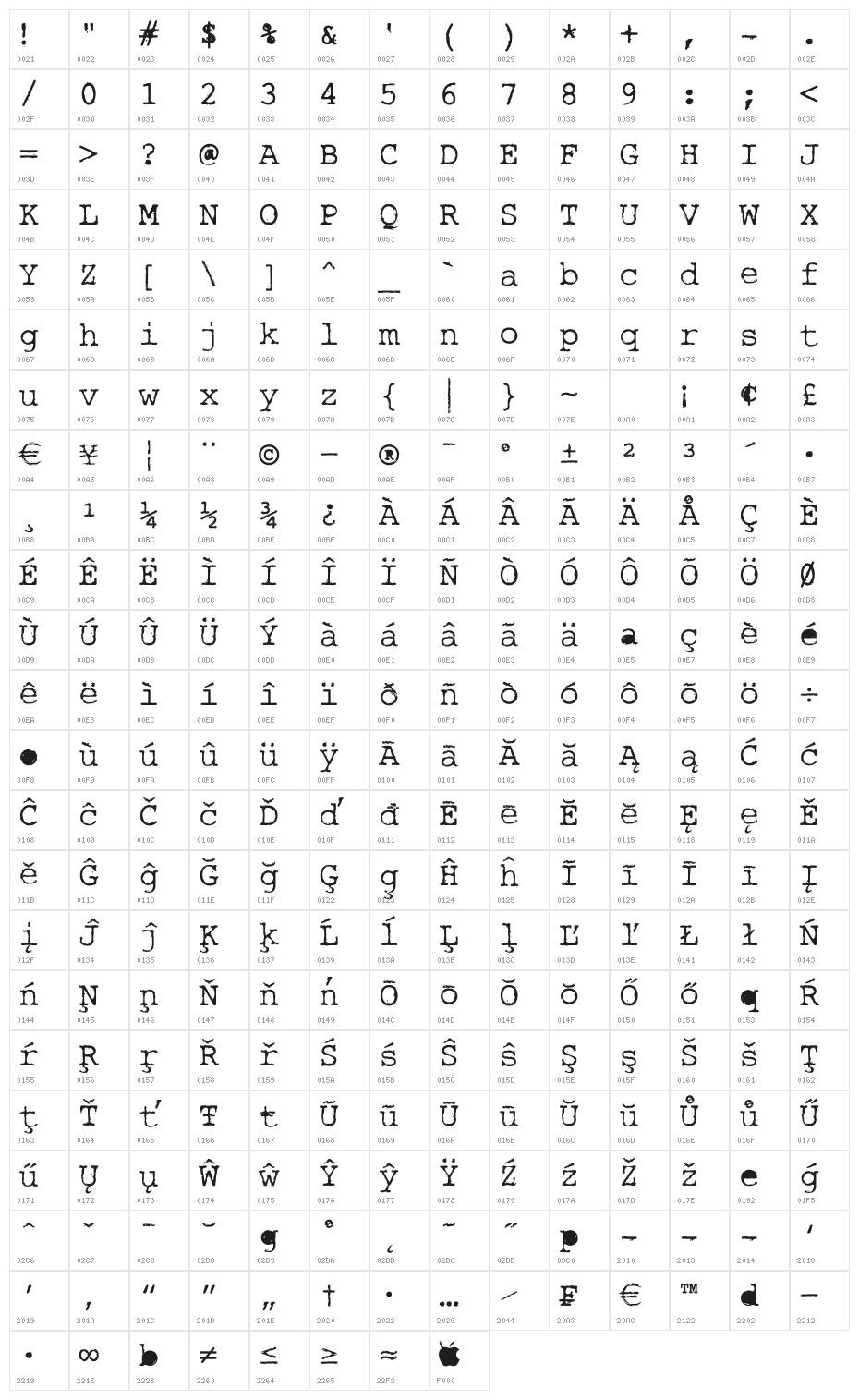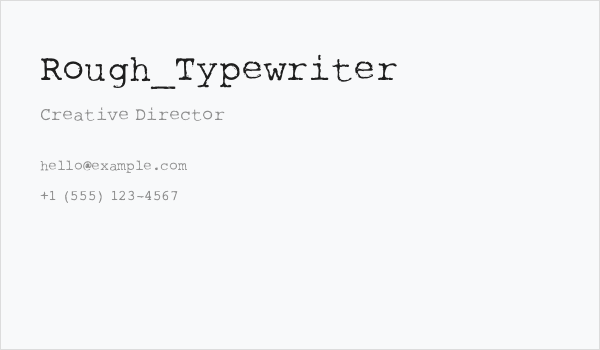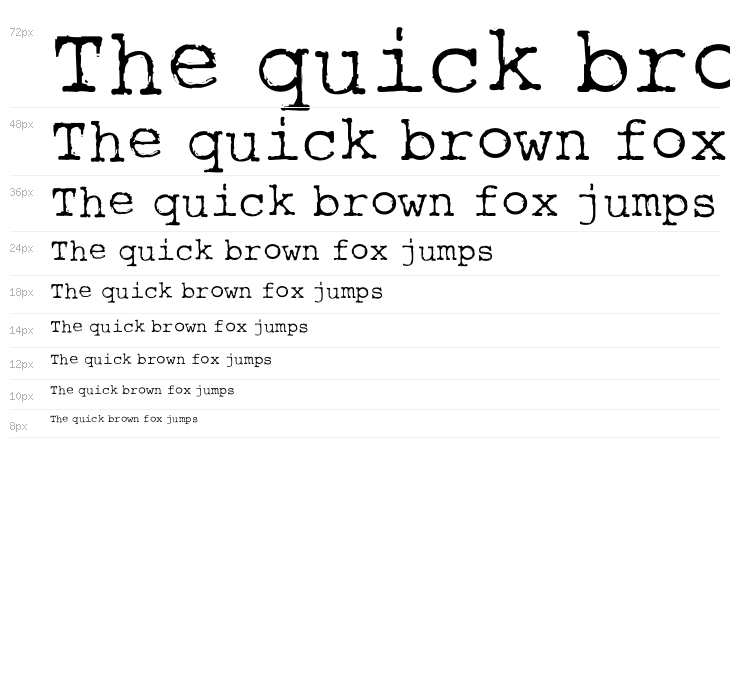
Rough_Typewriter Font
✎ Typewriter
| Kategorien | Typewriter |
| Gesamtstil | Vintage |
| Vorgeschlagene Projekte | Ideal for vintage-themed designs, retro posters, typewriter-inspired artwork, and projects requiring an industrial or historical aesthetic. |